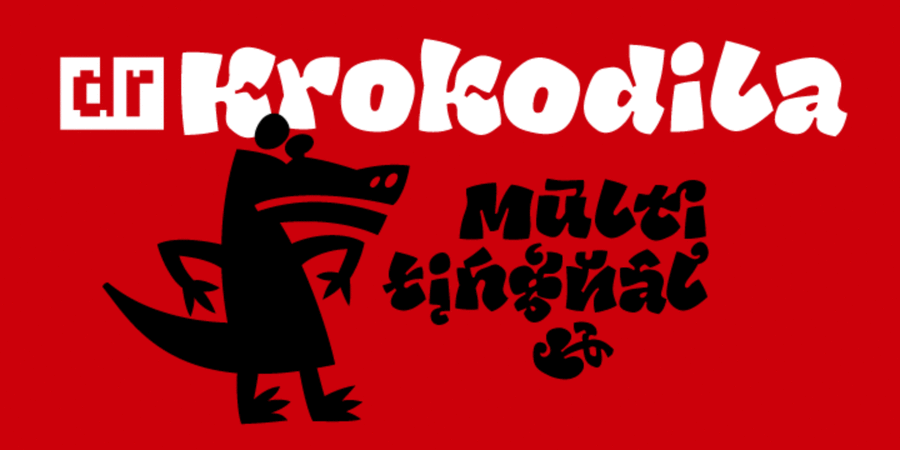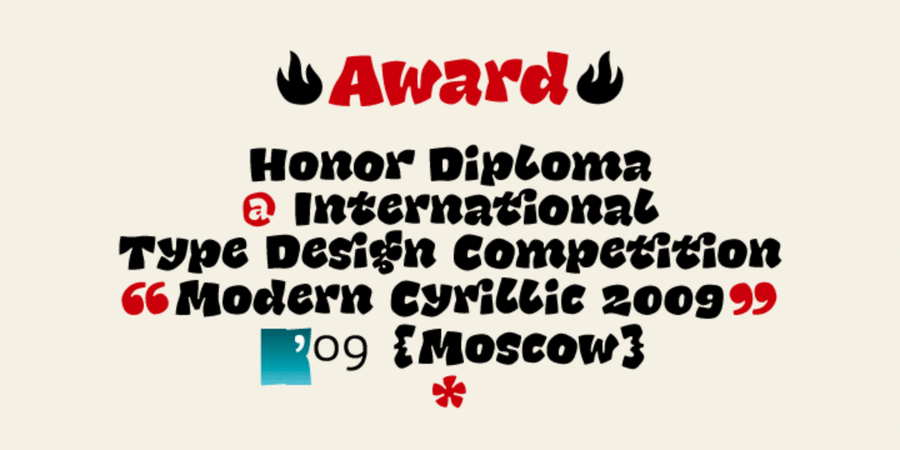
DR Krokodila (1 шрифт)
Шрифт Крокодила був розроблений Дмитром Растворцевим у 2009 році на прохання харківського видавництва "Мікко". Потрібен був прикольний дитячий шрифт для книжкової обкладинки. Таких шрифтів завжди дуже не вистачало, особливо з кирилицею.
Асоціації з сімейством шрифтів DR KrokodilaОсобистість і характер гарнітури:
веселий, важкий, помітний, яскравий, тісний, гучний, задерикуватий, смішний, стрибучий, неохайний, грайливий, пустотливий, непосидючий, рухливий, оригінальний, динамічний, стиглий, смачний, жований, дитячий, наївний, карикатурний, зубастий, мультяшний, звіриний, спекотний, південний, прикольний, дикий, навіжений, живий, неслухняний, грубий, характерний, неотесаний, нерівний, гулящий, дозвільний, пещений, сильний, ненажерливий, активний, дотепний, літній, тропічний, недбалий, дивний